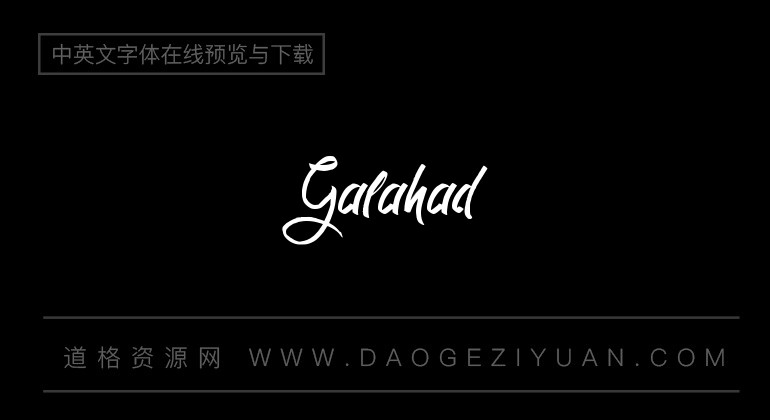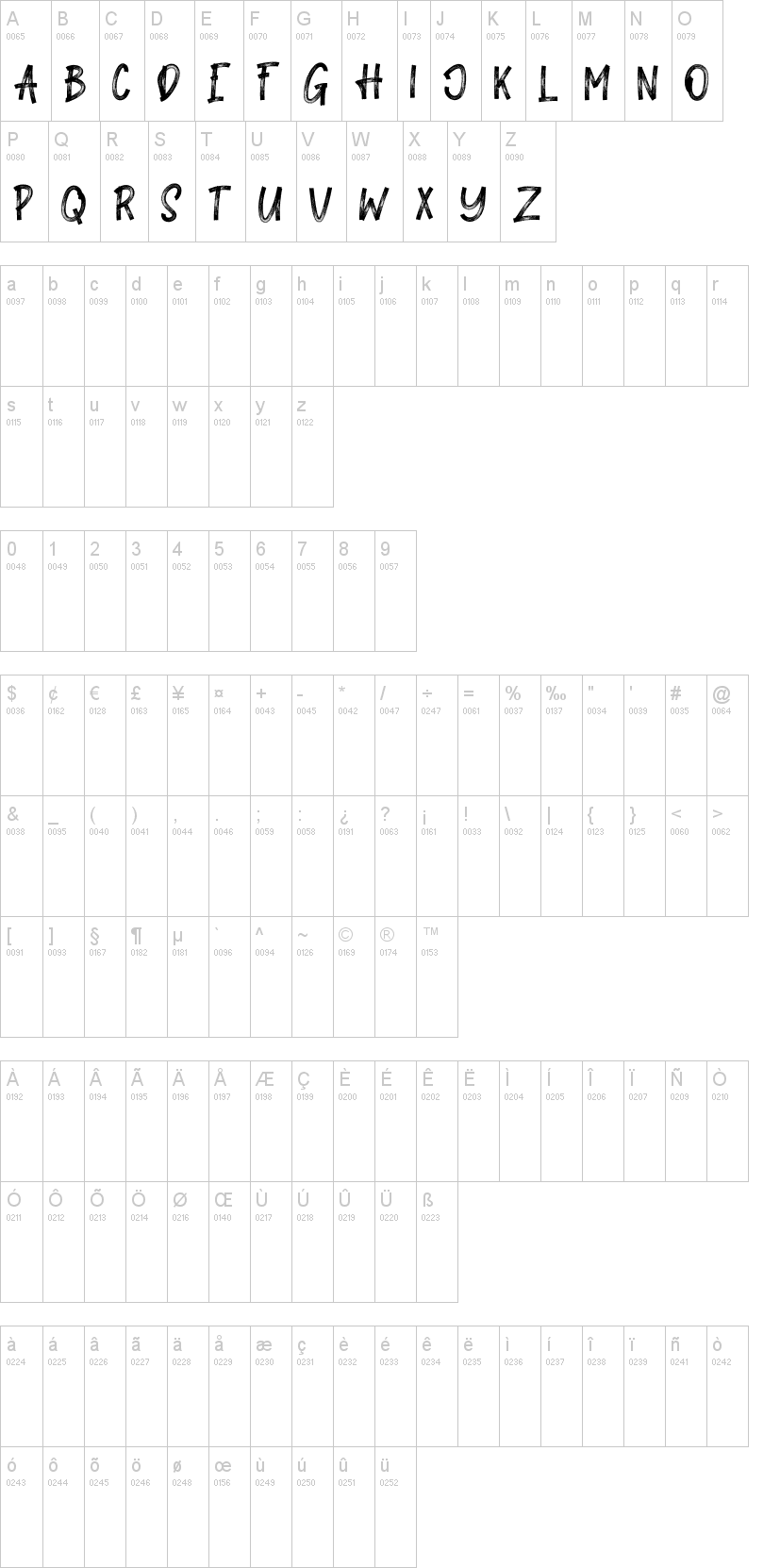
Galahad 是一款经典的字体,由英国设计师Frederic W. Goudy在20世纪20年代初创作。它的特点是细节丰富,有着温柔的曲线和流畅的行距。它也有着优雅的结构,可以为文字提供美观的排版。Galahad 字体是传统的字体,可以用于各种类型的文字,尤其适合用于书籍、杂志、报纸等文字排版。内容介绍
Galahad是一款非常不错的手写艺术字体,具有很好的视觉感,适合于文化类的宣传设计、商业类品牌的广告和产品包装设计以及个性化文字排版等较多场景。